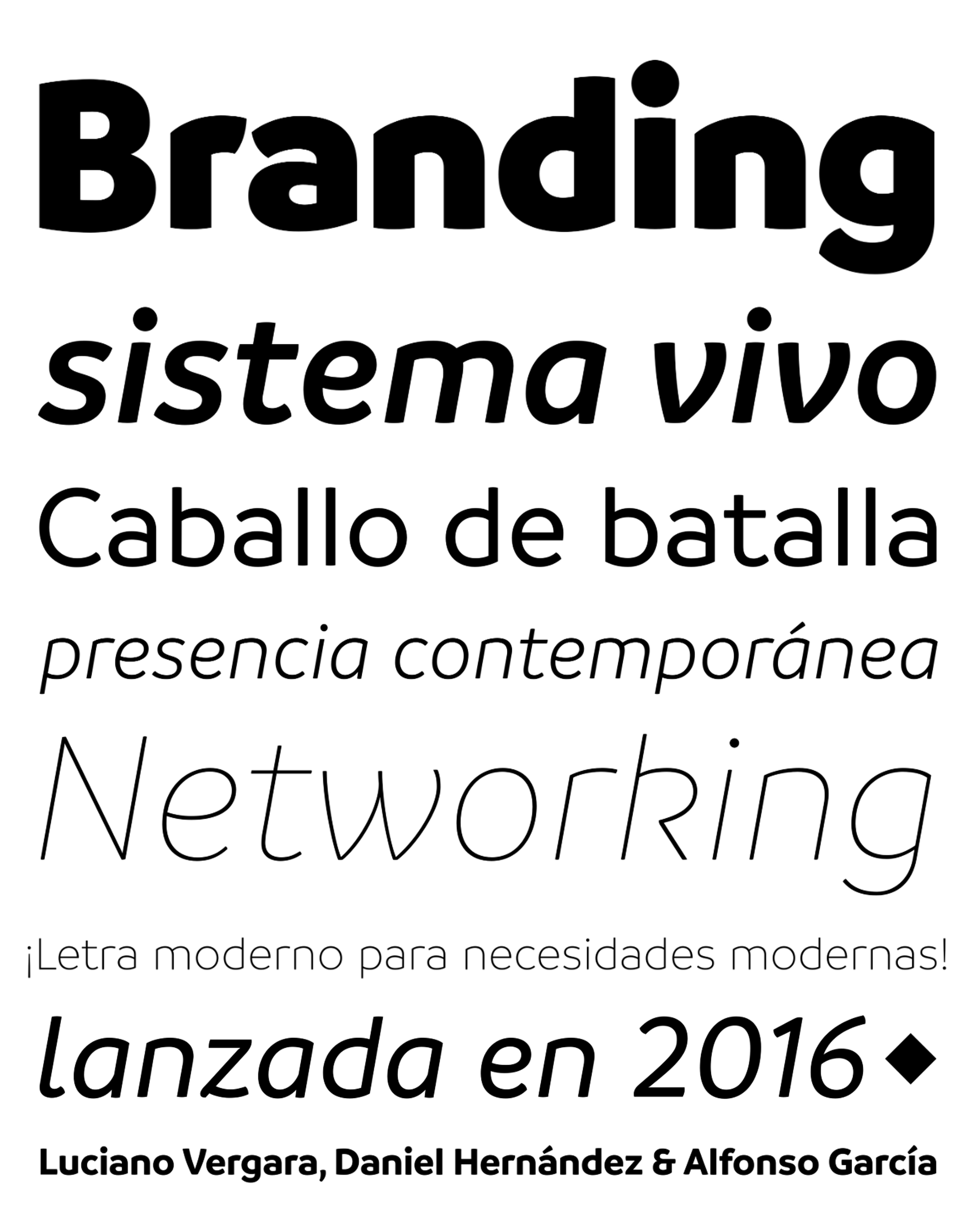
| Año | 2016 |
| Créditos | Luciano Vergara, Daniel Hernández, Alfonso García, Latinotype Team |
| Descripción | Branding, ¡un tipo de letra moderno para necesidades modernas! Branding, especialmente diseñado para satisfacer las necesidades estéticas y funcionales contemporáneas, es la interpretación de un tipo de letra moderno desde la perspectiva del propio diseñador. Este tipo de letra encierra una amplia gama de matices y combina, aparentemente, elementos opuestos como la tecnología y formas redondeadas amables. Además, los caracteres alternativos hacen de Branding una herramienta ideal tanto para diseñadores gráficos como para directores artísticos. Branding es un tipo de letra sans-serif sin espolones con una altura x media-grande, proporciones horizontales ligeramente más anchas, curvas rectas y terminales convexos. Esta fuente es adecuada para logotipos, isotipos, textos cortos, etc. Branding se presenta en 7 pesos -desde Thin a Black- con cursiva a juego e incluye un juego de 544 caracteres compatible con 128 idiomas diferentes. También se incluyen acentos europeos, números de estilo antiguo y múltiples alternativas. |
| Familia(s) | Thin, Thin Italic, Light, Light Italic, SemiLight, SemiLight Italic, Medium, Medium Italic, SemiBold, SemiBold Italic, Bold, Bold Italic, Black, Black Italic |
| Estilos | 14 |